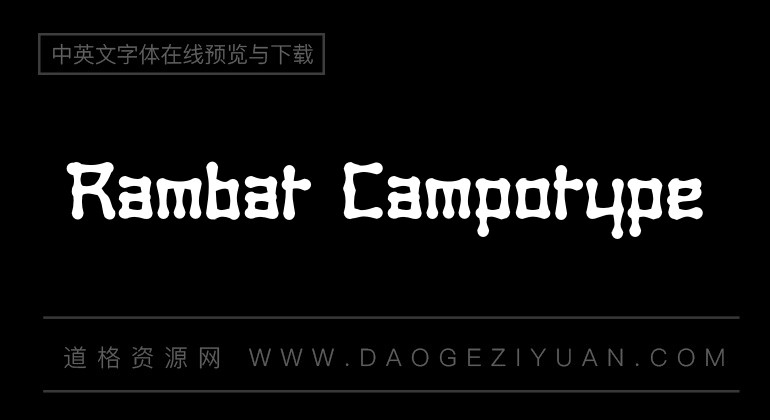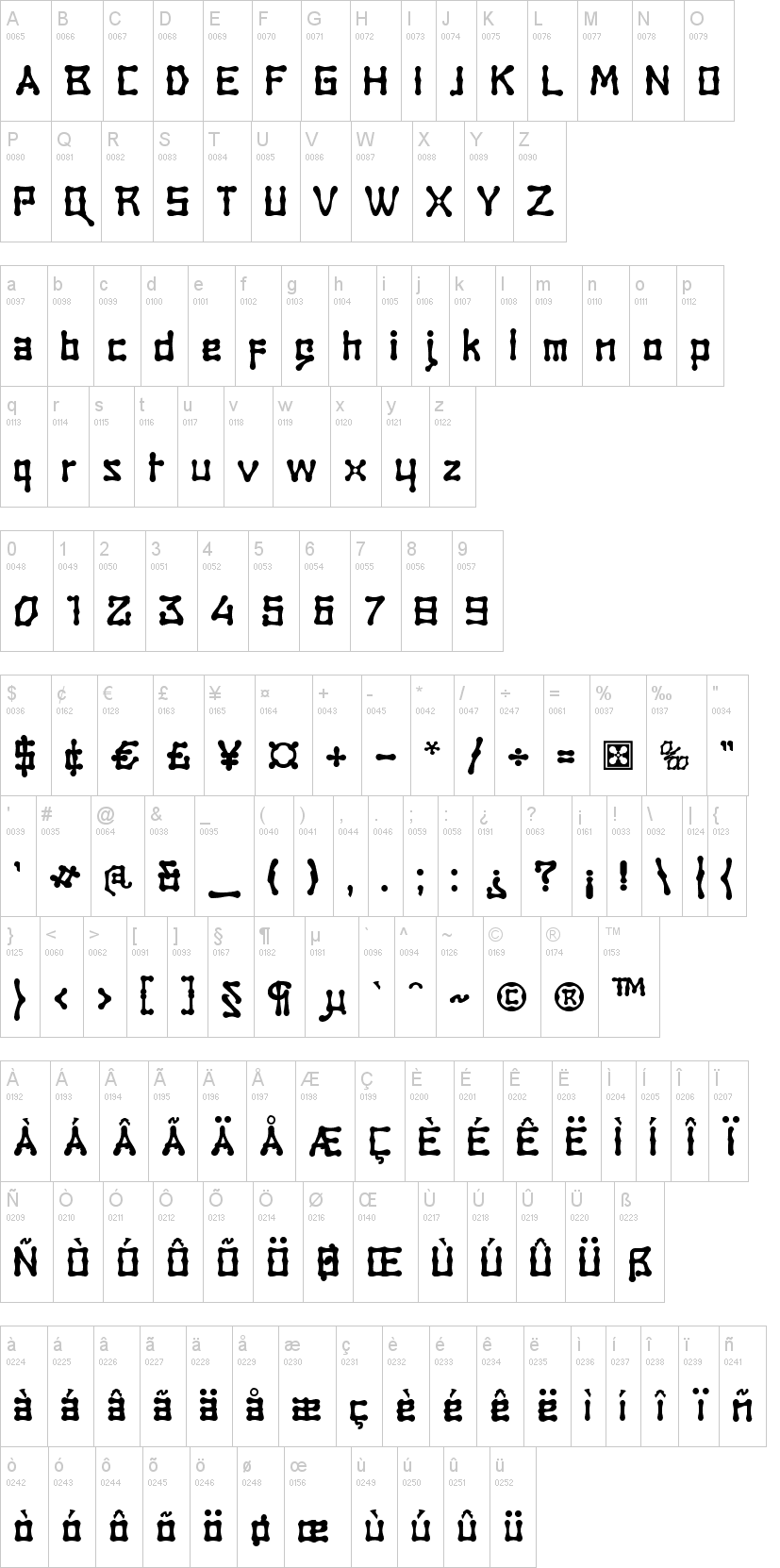
Rambat Campotype
? Rambat Campotype 字体是一款荷兰设计师 Ram Bat 创作的字体,它是一种体积极大、外形规整的粗体字体。这种字体具有极强的可读性,适用于标题、标识等场景。Rambat Campotype 字体的特点是,字符的细节比较多,比如他们有不同高度和宽度的字母,这使得它们看起来更加有活力。另外,这种字体也具有良好的空间感,能够更好地填补文本中的空白。
Rambat Campotype是一款非常不错的手写艺术字体,具有很好的视觉感,适合于文化类的宣传设计、商业类品牌的广告和产品包装设计以及个性化文字排版等较多场景。
Rambat Campotype字符映射图